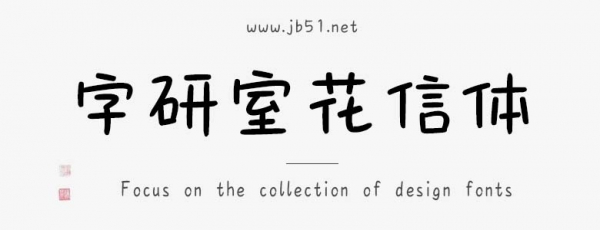
字研室花信體是字研室出品的藝術(shù)字體,字體筆觸適中,字形圓潤(rùn),具有很好的視覺(jué)感,適合應(yīng)用于藝術(shù)設(shè)計(jì)、平面宣傳設(shè)計(jì)、網(wǎng)頁(yè)設(shè)計(jì),書(shū)法字帖等領(lǐng)域。有需要的朋友快來(lái)本站下載使用吧。